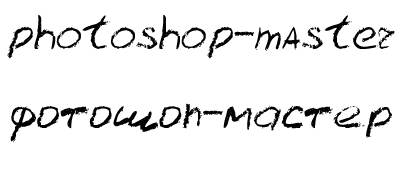
Шикарный шрифт,спасибо :3
если писать на чёрном фоне красным цветом, кажется, что написали помадой на стекле;D
Очень прикольный шрифт!!
хороший шрифт, мне нравится))
Мой любимый шрифт! ^_^